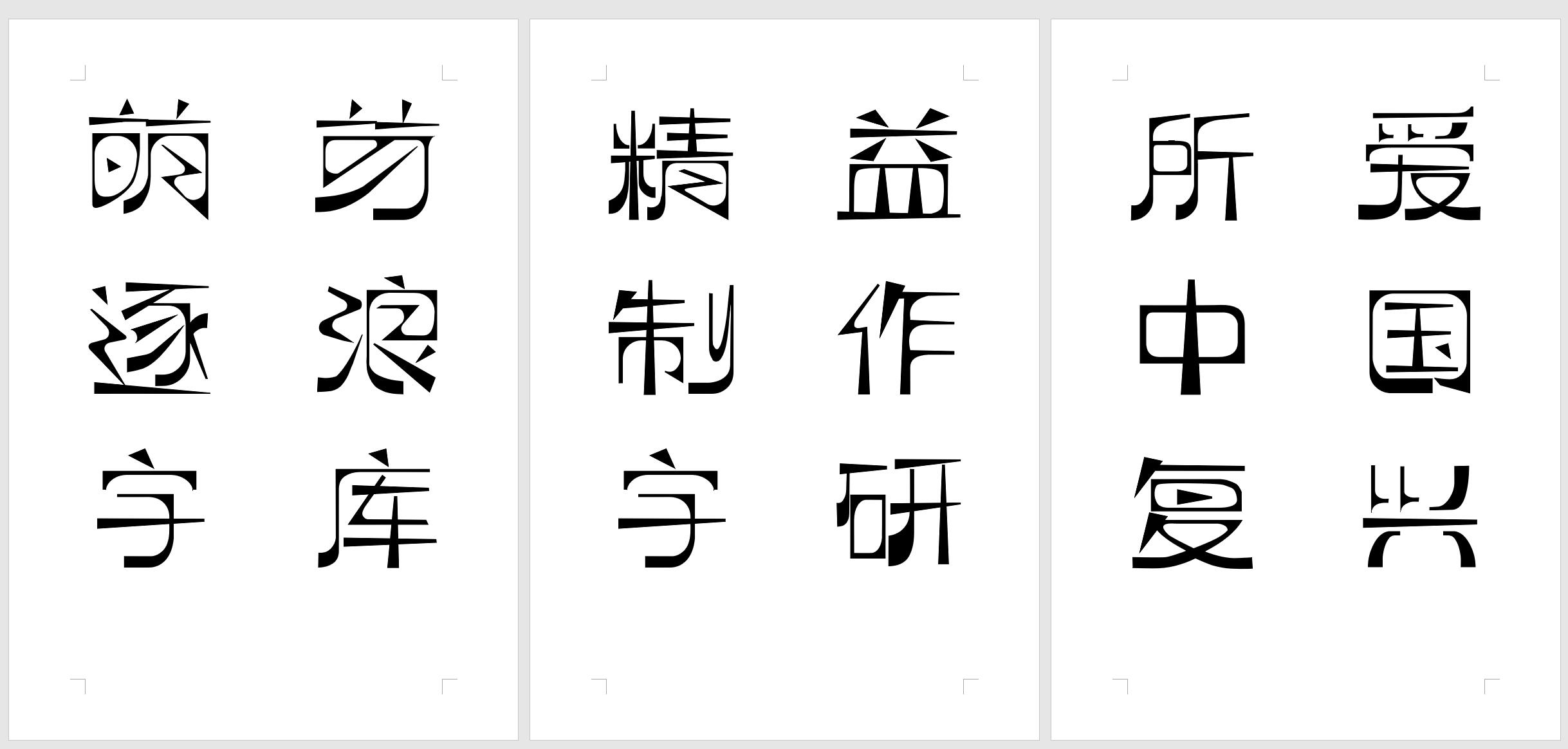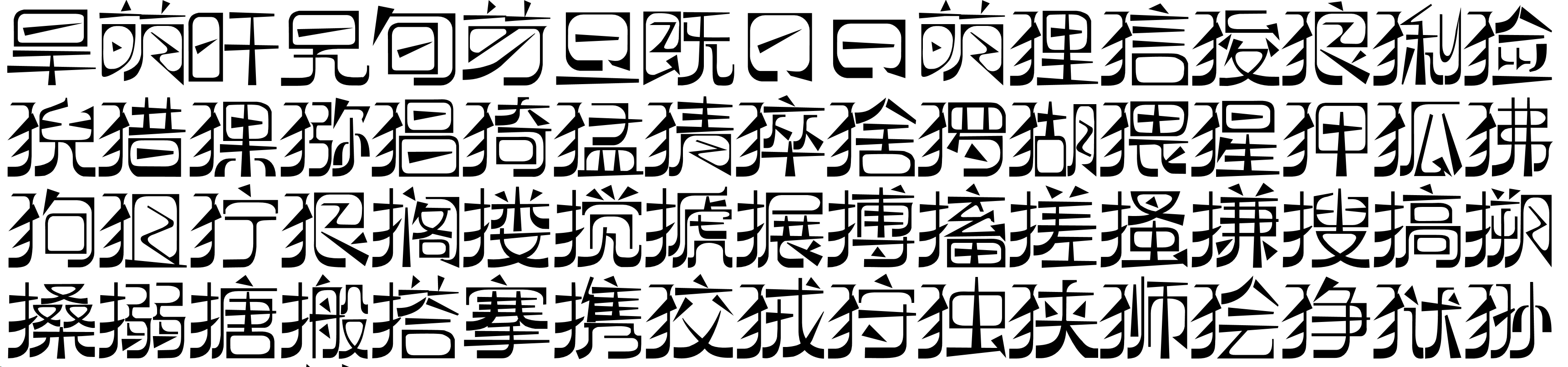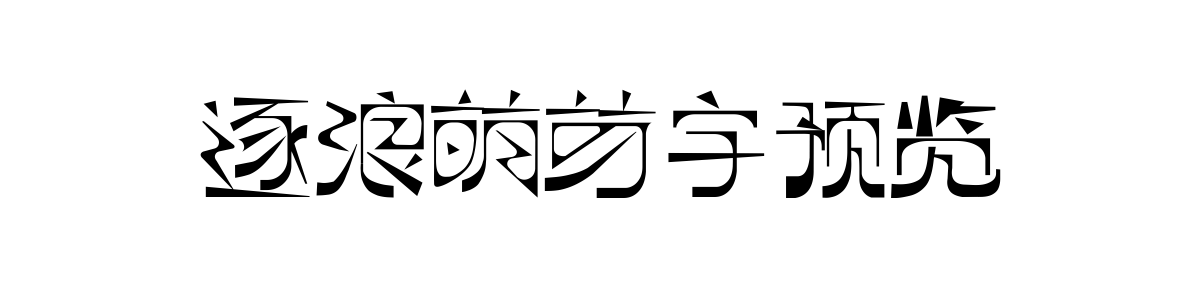
逐浪萌芽字
逐浪萌芽字(ZoomlaMengyas)是一款参照借鉴近代中国共产党《萌芽》月刊的艺术字体,源自五四运动文化,力求体现近代文艺风,以独特的字形语言复刻与诠释五四运动至左联时期那种简朴、刚健且充满理想主义激情的视觉风貌。
该字体由逐浪字库团队制作,其中文部分遵循 GB2312 标准,收录了满足日常使用的规范汉字;西文与拉丁字符部分符合 Google Fonts 的开源规范。
字体风格
逐浪萌芽字的设计充满了象征性与冲突感:外角尖锐如锋,内角圆润如弧,形成强烈的“外方内圆”视觉格局。字形整体被刻意压缩为矮宽方正的形态,流露出早期印刷品特有的朴拙与力量。
笔画处理上极具戏剧性:横画左粗右细,竖画上细下粗,在角部则加粗强调,形成了鲜明的粗细对比与动态张力。大量出现的三角形部件与弧形切割,抽象地融合了工业机械的硬朗与手写艺术的随性,共同指向一种上进、革命、进击的精神气质。